文字是设计中的重要一环
对文字进行创意处理
可以创造出富有视觉冲击力的字体
汉字设计更如是
在现代美学理念及其形式风格的影响下
汉字设计越来越强调
点、线、面、形、色和质感等
视觉要素的综合运用
那么常见的汉字设计手法有哪些呢
图文结合
在汉字设计中
图和字可以共用某种形态来表现
使图文相互融合
图文结合后可分为两种:
饰字图形
意字图形
前者以物形替代文字中的
某一笔画或某个字
后者将文字笔画做巧妙的处理
创造出意象化的文字
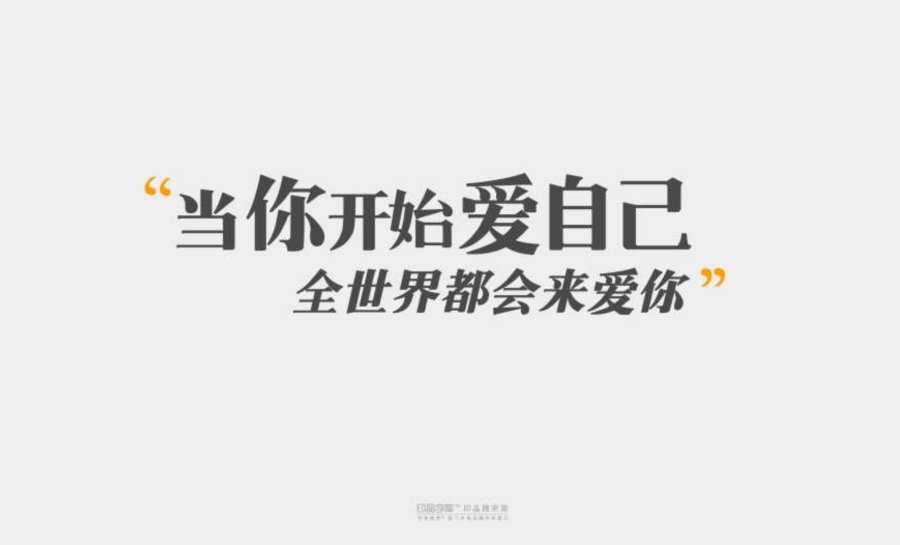
断笔
想要增加字体个性与趣味
断笔是一个有效的方法
当然断笔的前提
是不影响字的可读性
因此断笔要断在次要的笔画上
而不能断在主要笔画上
做到笔断意连
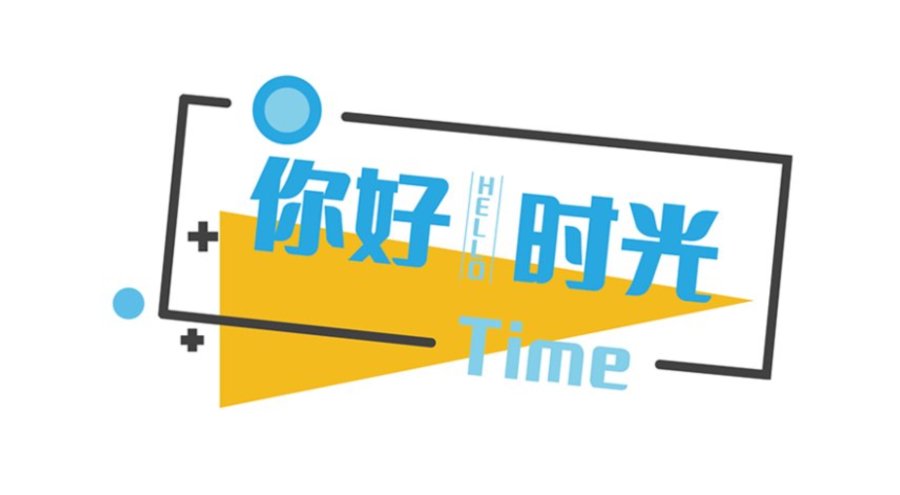
借笔
借笔指的是
字与字之间进行部分笔画的
相互借用和组合
互相融入对方的形体中
组成有机整体
借笔可以使信息传达更加便捷准确
同时还可以表现多重寓意
连笔
连笔指的是
一行文字的笔画不中断
以产生延绵不绝灵动活跃的美感
不过在设计过程中
线条之间必须自然简洁流畅
否则就容易繁琐零乱
编排
编排是对文字进行
自由的拼合和重构
在不影响阅读体验的前提下
新颖创意的编排方式
是现代视觉传达设计中的一种时尚
最终目的是为了
呈现完美的视觉效果
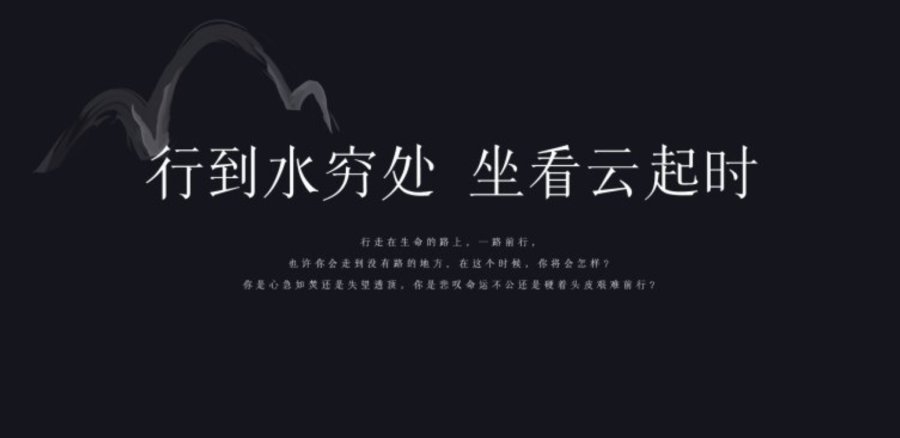
图底互换
图底互换会带来意趣盎然的效果
在平面设计中
图与底是反转互换的
而在汉字设计中
在图底互换前
首先要让字距与大小匀称分布字库下载
让图与底面积相似
如此
图与底才会随着
观者注意部位的变换而转换
嫁接
嫁接指的是
将拉丁文字体、古典罗马体、埃及体等
多种不同类型字体的特点
移植到汉字字体设计中
获取新颖奇特的效果
点状
点的面积虽小
却能表达丰富的趣味
点移动产生线
点聚集产生面
将点的手法运用到汉字设计中
可以组成几何形状或自由自在的形态
变异
变异的字体图形
指的是文字与图形在演化中
相互转化与结合
形成新的组合
产生奇特有趣的效果
光影
在文字设计中
运用光影的构成方法
可以创造具有三维立体感的形态
明暗分明的光线分布
也可以让复杂的文字图形
变得整齐统一层次分明
需要注意的是
在设计光影文字图形时
要让暗与亮互相衬托与塑造
使其形影不离
空间
空间指的是利用字形
高宽透视变化
达到三维立体空间效果
这种空间并非真实存在
而是通过字体图形对人的视觉引导
形成的虚拟空间